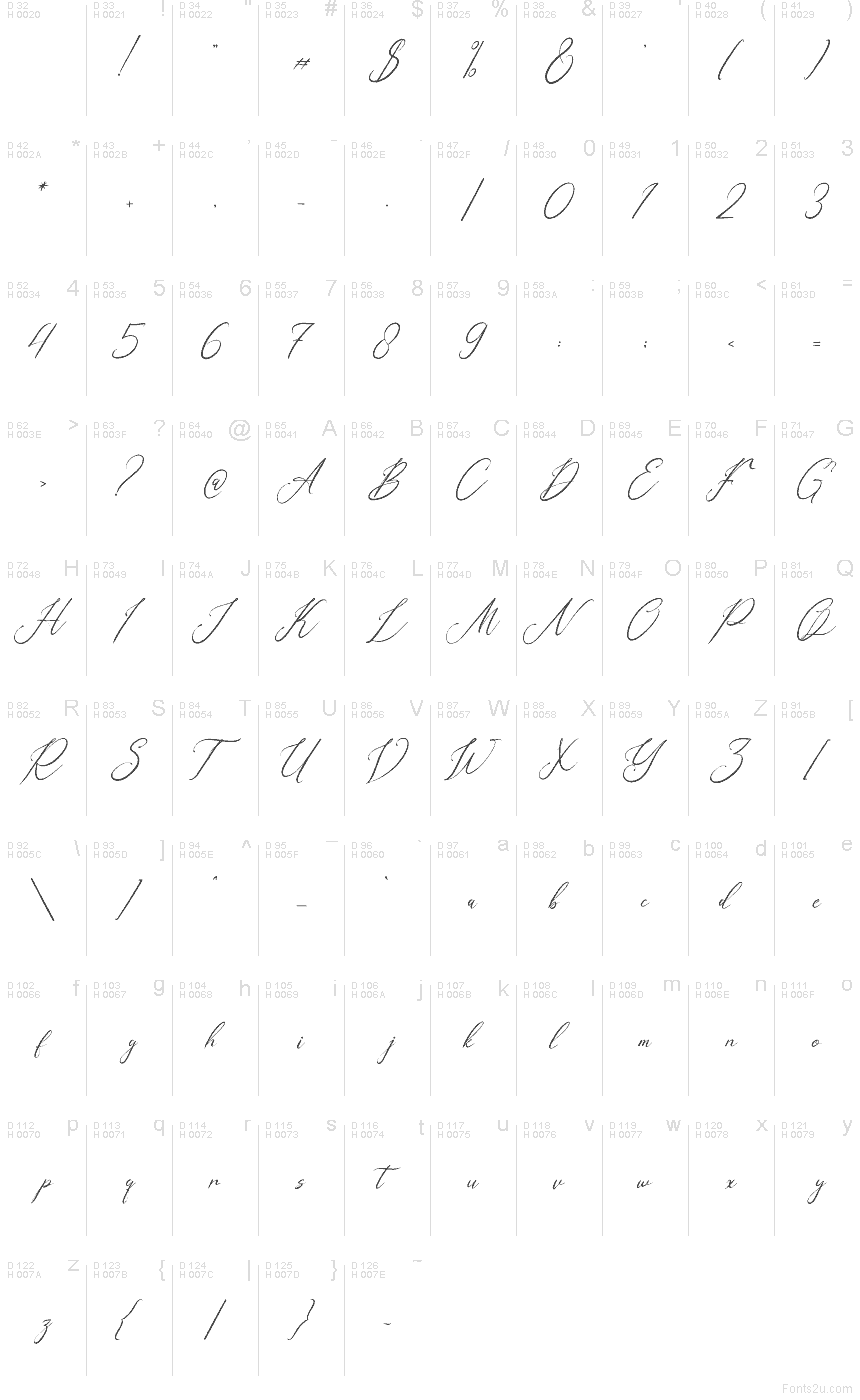
Geraldyn Brushko
Geraldyn Brushko de Denustudios est une police calligraphique gratuite, façonnée par de longues boucles aériennes et un rythme manuscrit fluide. Son tracé d'entrée balayé et ses hampes fines et ascendantes confèrent aux lettres une élégance naturelle, évoquant davantage le mouvement spontané de l'encre qu'une calligraphie formelle.
Ce dynamisme est idéal pour les faire-part de mariage, l'image de marque beauté, le packaging de boutique, les logos signature et les visuels de citations pour les réseaux sociaux où une touche douce et personnelle est essentielle. Elle se distingue particulièrement dans les titres courts et les designs centrés sur les noms, car ses fioritures intégrées habillent chaque mot sans nécessiter d'ornements supplémentaires.